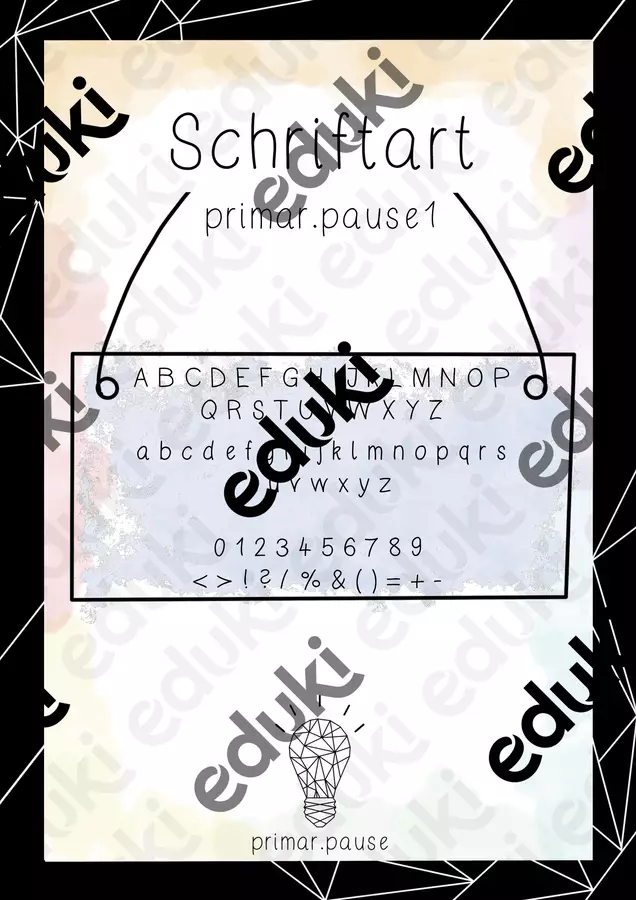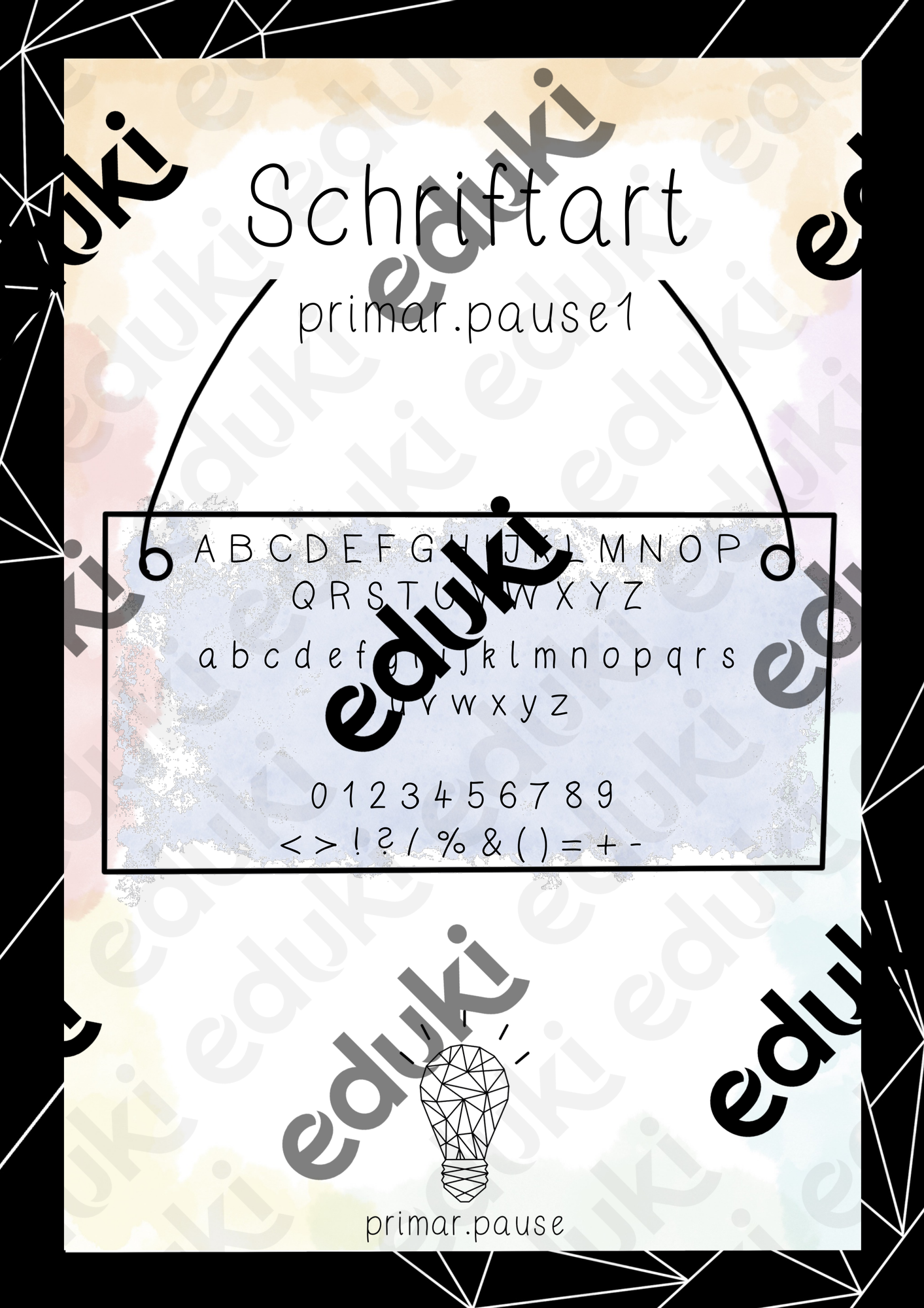
Hier findest du unsere schlichte Primar.Pause - Schrift, die du sowohl privat als auch kommerziell im Bildungsbereich nutzen darfst.
Schriftart Primar.Pause1